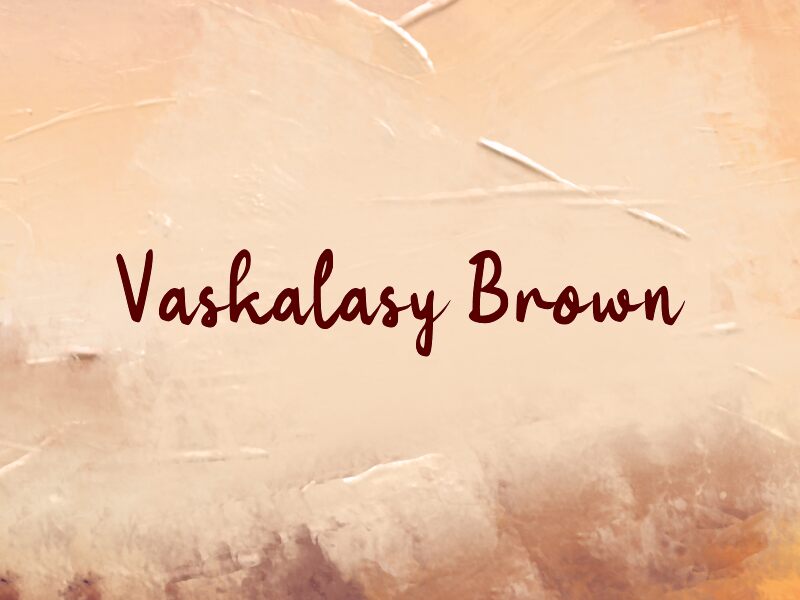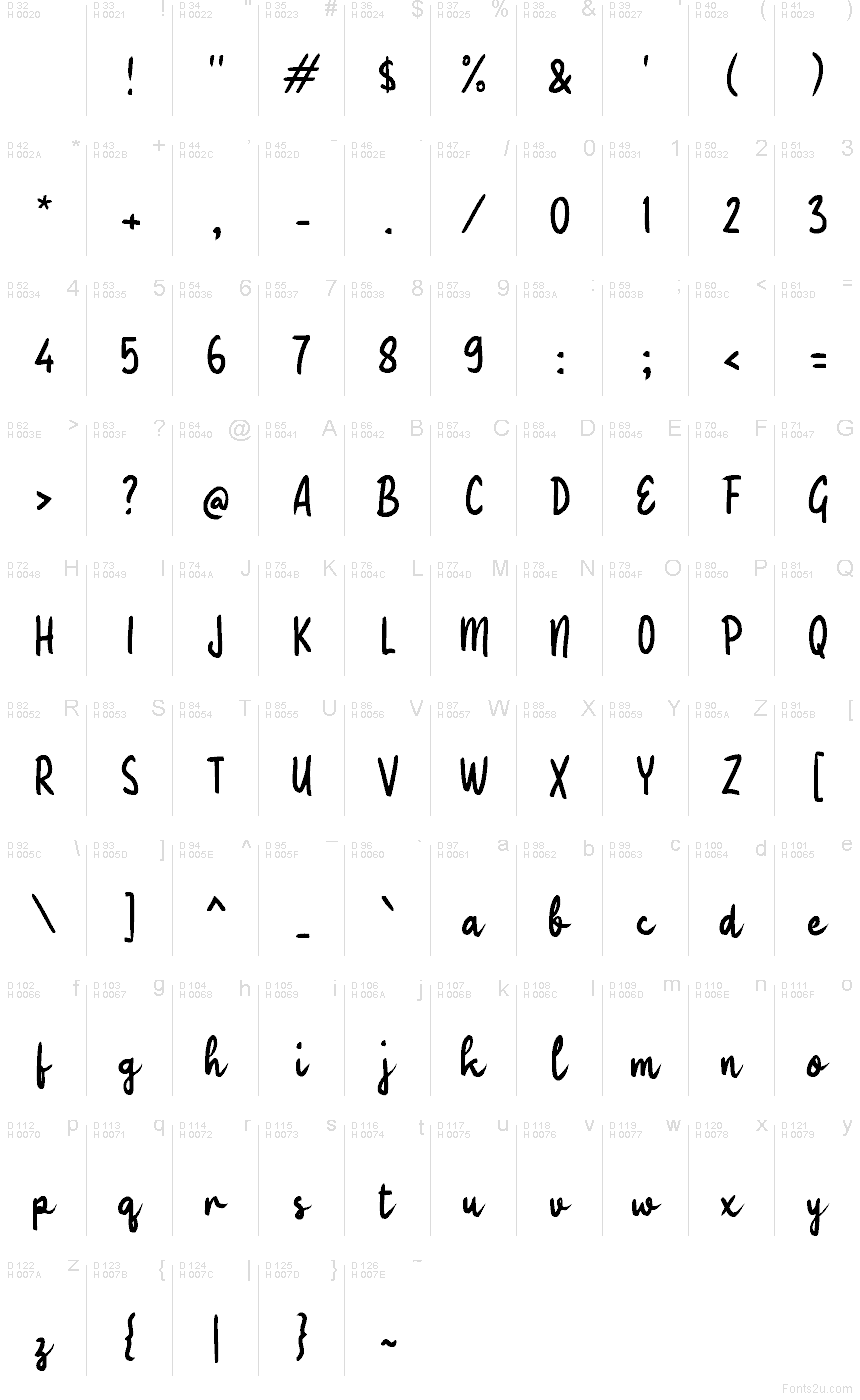
Vaskalasy Brown
Vaskalasy Brown di Wep è un font scritto a mano gratuito dallo stile immediato, simile a una pennellata. Le lettere presentano tratti spessi e arrotondati con legature rapide, che conferiscono alla linea un ritmo informale, come se fosse stato scritto d'un fiato anziché disegnato con cura.
È perfetto per post sui social, branding di caffetterie, packaging, loghi casual e brevi titoli per poster, dove un tono caldo e personale è più importante della perfezione formale. Essendo un font gratuito, funziona bene anche per titoli o citazioni d'impatto: i tratti ampi e le curve morbide rendono anche le parole brevi vivaci e rilassate.